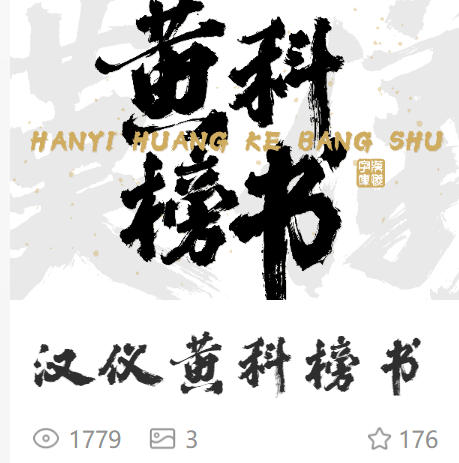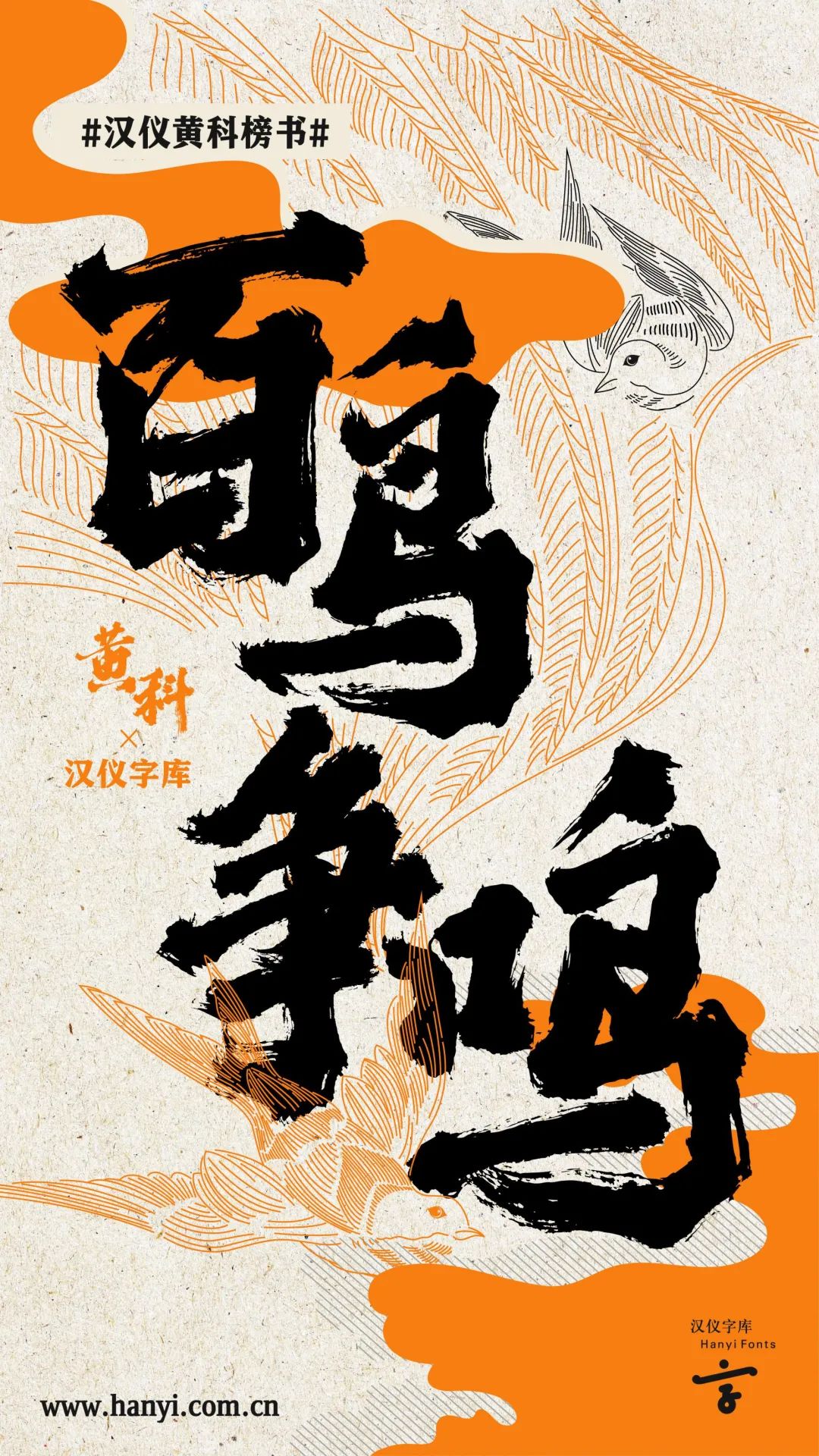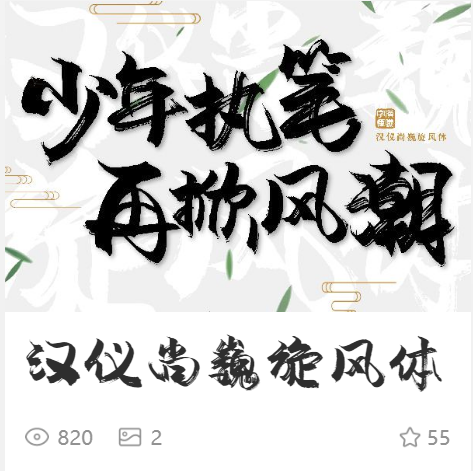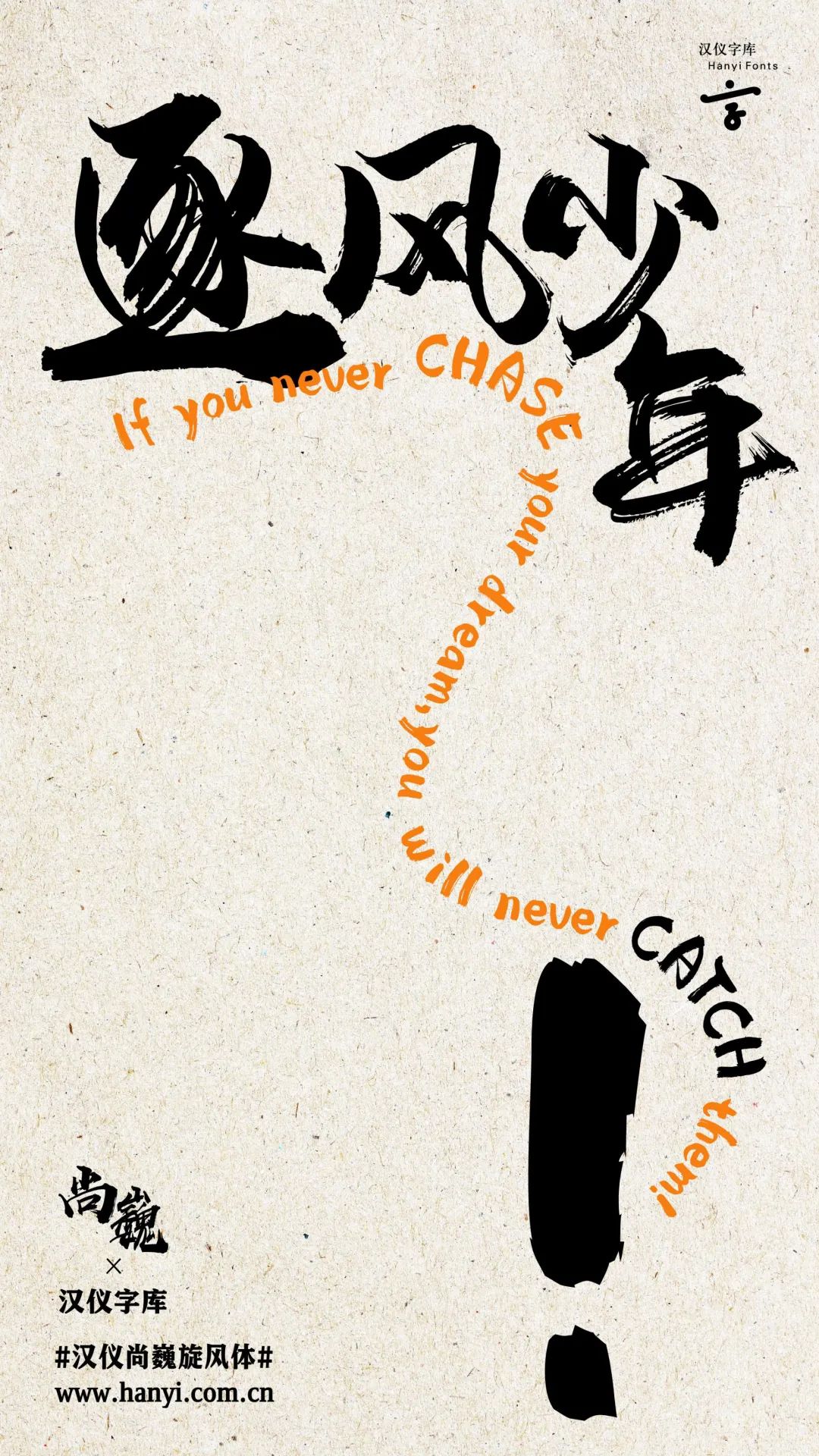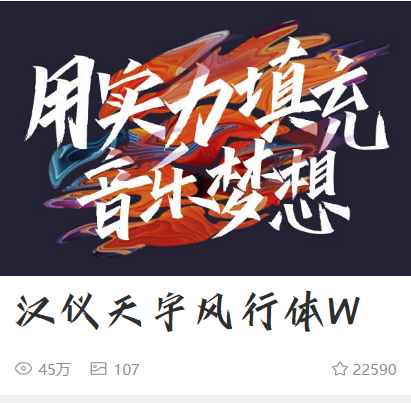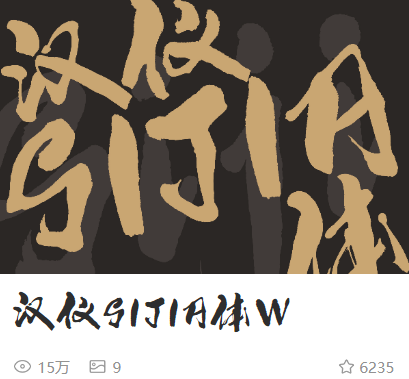
让人欲罢不能的国潮,都在用什么字体?
这几年国潮的热度一直只增不减,够美,够劲,够霸气!
这其中字体功不可没,毕竟少了它,就没内味了,今天柚子就给你推荐几款~
汉仪黄科榜书
汉仪字库签约青年手写人 黄科
中文字体 刘其龙
西文字体 刘嫣然
汉仪黄科榜书的特点也可以归纳为“大”。第一是作者书写时的“大”,一个字一张纸,一共书写了九千余张;第二个是字库大,这款字尽量保留了书写时丰富的笔触,做到了最大程度的细节还原;第三是风格豪放大气,非常适合放大使用。
汉仪尚巍旋风体
汉仪字库签约青年手写人 尚巍
中文字体 刘其龙
西文字体 刘嫣然
那个凭汉仪尚巍手书一炮而红的尚巍,又出字体了,这次不同于其他手写体,加重了手写的速度感,“旋风”顾名思义,字体的笔画、造型都犹如一阵风吹过,走路带风,表现了字体的力量感与速度感。
除了新上的这两款,字由还有其它国潮字体,比如秦川的两款。
尚巍的两款~
天宇、sijia、迪升各一款~